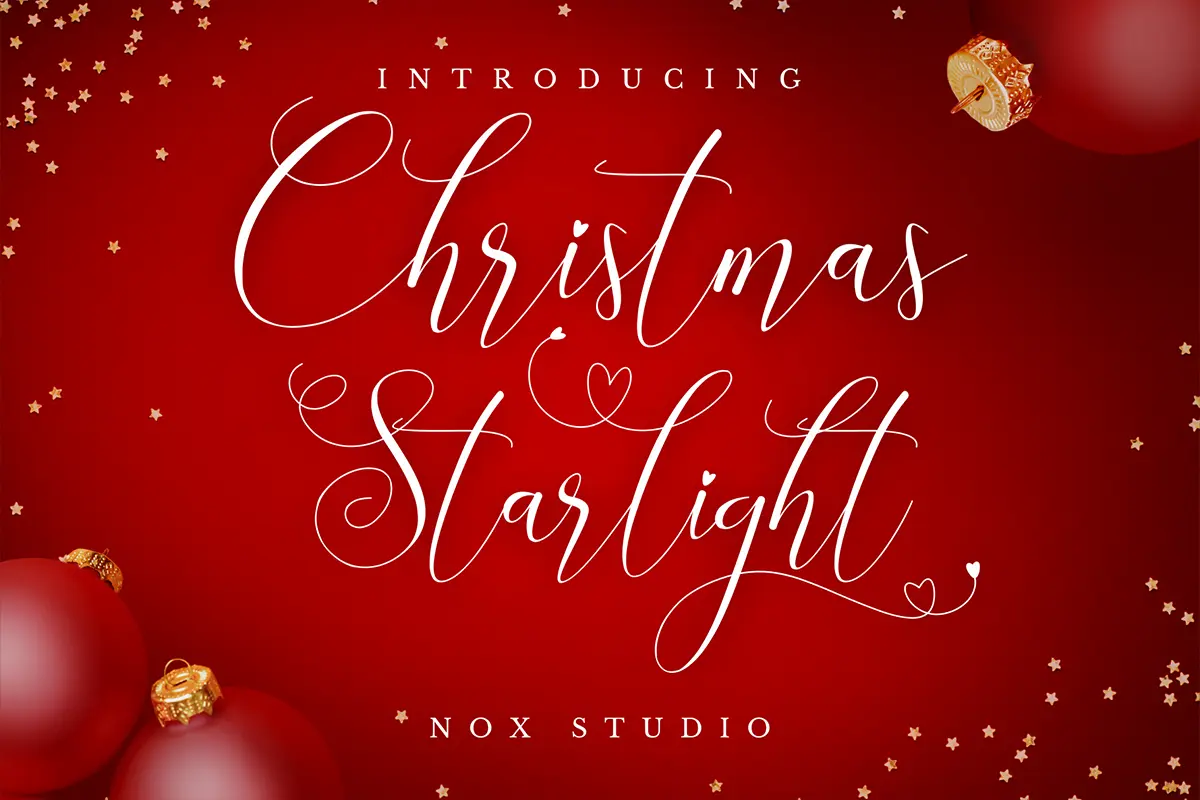
فونت رمانتیک کریسمس
فونت رمانتیک Christmas Starlight یک فونت دست نویس درخشان و ماندگار است که جلوهای چشمگیر و هنری به طراحیهای شما میبخشد. این فونت برای پروژههایی که نیاز به حس گرم، جشن و جذابیت دارند انتخابی عالی محسوب میشود و میتواند طراحیهای شما را حرفهایتر و متفاوتتر نشان دهد.
⭐ ویژگیهای محصول
- سبک دستنویس زیبا و درخشان
- مناسب برای طراحیهای لوگو، برندینگ و نقلقولها
- انتخابی عالی برای کارتهای تبریک و پروژههای مناسبتی
- جلوهای خاص و چشمگیر برای هر نوع طراحی
🎯 موارد استفاده
- طراحی لوگوهای خلاقانه و مناسبتی
- ساخت کارتهای تبریک کریسمس و سال نو
- استفاده در برندینگ و تبلیغات جشنها
- افزودن به پورتفولیو طراحان گرافیک
- مناسب برای پروژههای چاپی و دیجیتال